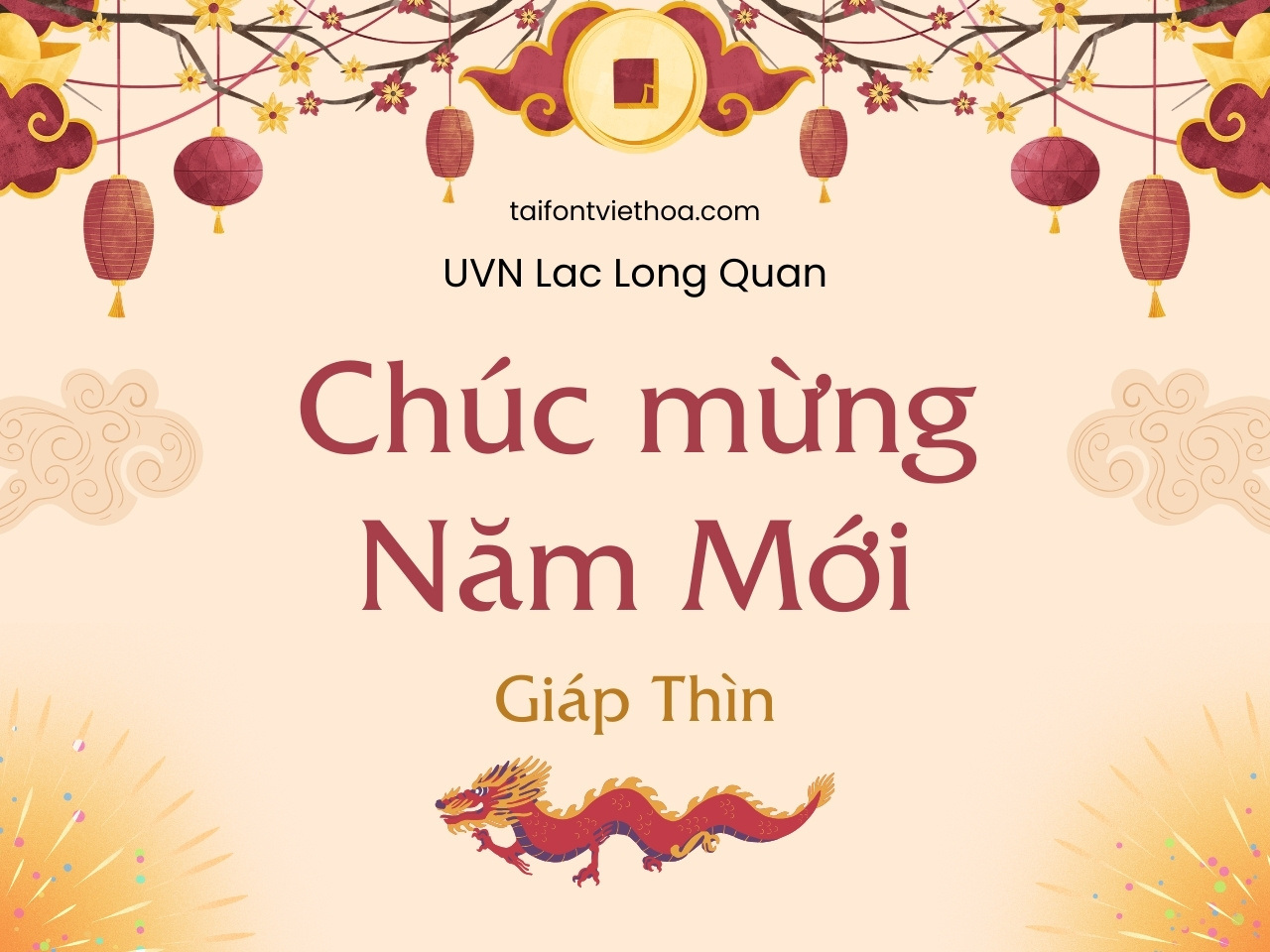
Font việt hóa UVN Lac Long Quan
Giới thiệu về font UVN Lac Long Quan
UVN Lac Long Quan là một font chữ đậm đà bản sắc Việt, lấy cảm hứng từ truyền thuyết dân gian về vị thủy tổ của người Việt – Lạc Long Quân. Font mang phong cách mạnh mẽ, rắn rỏi và cổ kính, thể hiện tinh thần lịch sử và văn hóa phương Đông qua từng nét chữ. Với yếu tố hoài cổ và phong thái uy nghi, UVN Lac Long Quan là lựa chọn lý tưởng cho các thiết kế mang tính dân tộc, truyền thống hoặc nội dung giáo dục lịch sử. Font được sưu tầm và chia sẻ bởi thành viên Font Chuẩn, đồng thời được taifontviethoa.com chọn lọc nhằm phục vụ cho các dự án thiết kế văn hóa, truyền thông cổ truyền và ấn phẩm lịch sử.
Đặc điểm thiết kế và ứng dụng của UVN Lac Long Quan
Font UVN Lac Long Quan có cấu trúc chữ cứng cáp, chắc chắn, với các nét gãy gọn, sắc cạnh và bố cục hài hòa. Kiểu dáng gợi nhớ đến các bảng hiệu cổ hoặc văn bản khắc gỗ truyền thống, mang lại cảm giác trầm mặc, trang nghiêm. Font hỗ trợ đầy đủ tiếng Việt, dễ sử dụng trong các thiết kế số cũng như in ấn quy mô lớn.
Ứng dụng lý tưởng: tiêu đề sách lịch sử, banner lễ hội văn hóa, thiết kế bảo tàng, logo sự kiện cổ truyền, ấn phẩm tuyên truyền di sản. Ngành nghề phù hợp: giáo dục, bảo tàng, truyền thông văn hóa, quảng bá lễ hội và các dự án di sản dân tộc.